漫画などの描き文字は除いています(手書きでは、あまり珍しくないため)。
- 来々妖魔奇譚っ! 雑誌掲載(1990年)
- 魔天童子(1990年)
- 来々妖魔奇譚っ! 単行本(1990年)
- 来々妖魔奇譚っL(1995年)
- 来々妖魔奇譚っL+30(2004年)
- 電撃「マ)王(2005年)
- 電撃黒「マ)王(2007年)
- すてマ!〜魔法少女拾いました〜 雑誌掲載(2012年)
- すてマ! 単行本(2013年)
- 魔法の女子高生(2016年)
- 小悪魔的カノジョ(2017年)
- 魔法少女さんだいめっ☆(2018年)
- 小悪魔ちゃんのこうげき!(2019年)
- 対魔忍TV(2020年)
- アイドル対魔忍(2021年)
- ゲー魔王(2022年)
- 対魔忍サプリ 対魔忍アサギ Energy Supplement(2023年)
- 推しが魔!(2024年)
- 対魔忍サプリ 水城ゆきかぜの雷撃energy(2024年)
- おしが魔法少女(2025年)
- 魔法童女よつぎ☆ピース(2026年)
来々妖魔奇譚っ!
雑誌掲載織倉まことの漫画で、初出は漫画雑誌「レモンピープル」1990年 No.112(3月号)1。7ページの題名のページでは「来々妖魔奇譚っ!!(前編)」となっている。一方、表紙では「新連載!! 来々妖魔譚!!」と、「奇」と「っ」を省いた題で紹介されている。どちらも「魔」が略字だが、字の形は異なる。
雑誌掲載時と初めての単行本では、作品名の「魔」をわざわざ广+マの略字で書いているが、決まったロゴはなく、表紙と本編で字の形が異なる。さらに、本編の吹き出しなどの写植でも「魔」を广+マにしており、作品全体で略字を通すこだわりが見られる。
魔天童子
クエストが1990年8月24日に発売した、ファミリーコンピュータ用のアクションゲーム1。中華風の横スクロールアクションで2、天上人最後の生き残り「天童」と「神犬ドドンパ」が、暗黒の覇者「灰冥王」を倒す旅に出る1。
ロゴはパッケージだけでなく、ゲームのタイトル画面でもドット絵で表現されており、どちらも「魔」が广+マの略字になっている1。
電撃「マ)王
メディアワークスが2005年10月27日に創刊した雑誌で、「ゲーム・コミック・ノベルの融合」をうたうエンタテインメント誌1。
誌名の「魔」は、正しくは广の中に丸で囲んだ「マ」を置いた形(广+○+マ)。表紙のロゴでは「マ」を八角形で囲んでいるが、表紙以外では、丸で囲んだ「マ」の形で植字されたり、見出しの文字にされたりしている2。
一方、創刊当時の公式ページ(Web)では、誌名を文字で「電撃「マ)王」と書いていた1。
公式サイト上の表記は、のちに「電撃マ王」と簡略化され、2011年12月号で誌名が「電撃マオウ」に変わった。2014年2月号までは、ロゴの右上に以前の表記が残されていた3。
電撃黒「マ)王
メディアワークスの「電撃「マ)王」の増刊として創刊された、「ちょっぴりオトナ、ちょっぴりエッチなコミック誌」。Vol.1 は電撃「マ)王 2007年10月号増刊として、2007年9月19日に発売された1。誌名の「黒」には「ブラック」のルビが振られ、「魔」は本誌と同じく广+○+マの形。
2010年6月22日発売の VOLUME12 で最終号となり、連載作品の一部は月刊電撃マ王に移籍した2。
すてマ!〜魔法少女拾いました〜
雑誌掲載原案は Magica Quartet、漫画は山田石人の4コマ漫画。「魔法少女まどか☆マギカ」のスピンオフで、まどかを救うために時間遡行を続けるほむらが、「捨て魔法少女」となってまどかに拾われる時間軸を描く1。
「魔法少女まどか☆マギカ」を専門に扱う漫画雑誌「まんがタイムきらら☆マギカ」(芳文社)で、創刊号の Vol.1(2012年6月8日発売)から連載された2,3,4。Vol.1 は国立国会図書館に未所蔵5。
上のロゴは単行本1巻に収録された連載第1回のもので、作者によると、雑誌掲載時はこのロゴのモノクロ版だったと思われるとのこと6。
単行本では題が「すてマ!」になり、ロゴも異なる。
すてマ!
単行本山田石人(原案: Magica Quartet)の「すてマ!〜魔法少女拾いました〜」の単行本で、まんがタイムKRコミックス(芳文社)から全3巻が刊行された1,2。1巻には、「まんがタイムきらら☆マギカ」Vol.1〜7と「まんがタイムきららフォワード」H24/12月号・H25/7月号に掲載されたものと、描き下ろしを収録3。
単行本では題が「すてマ!」になり、雑誌掲載時とはロゴが異なる。
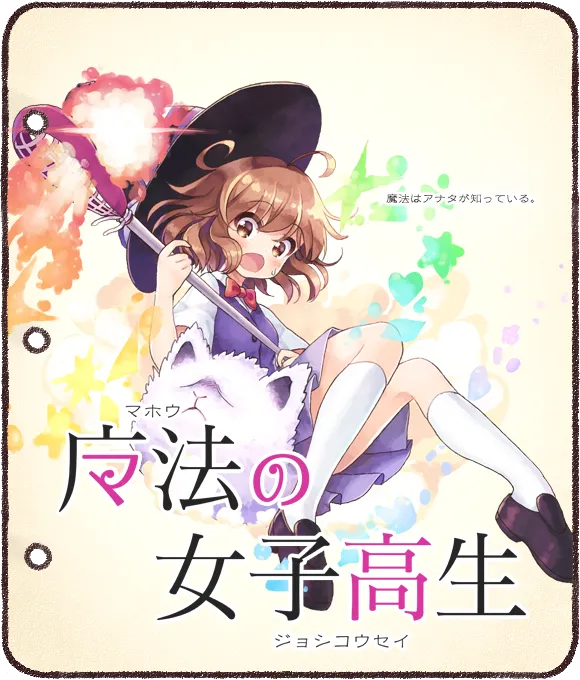
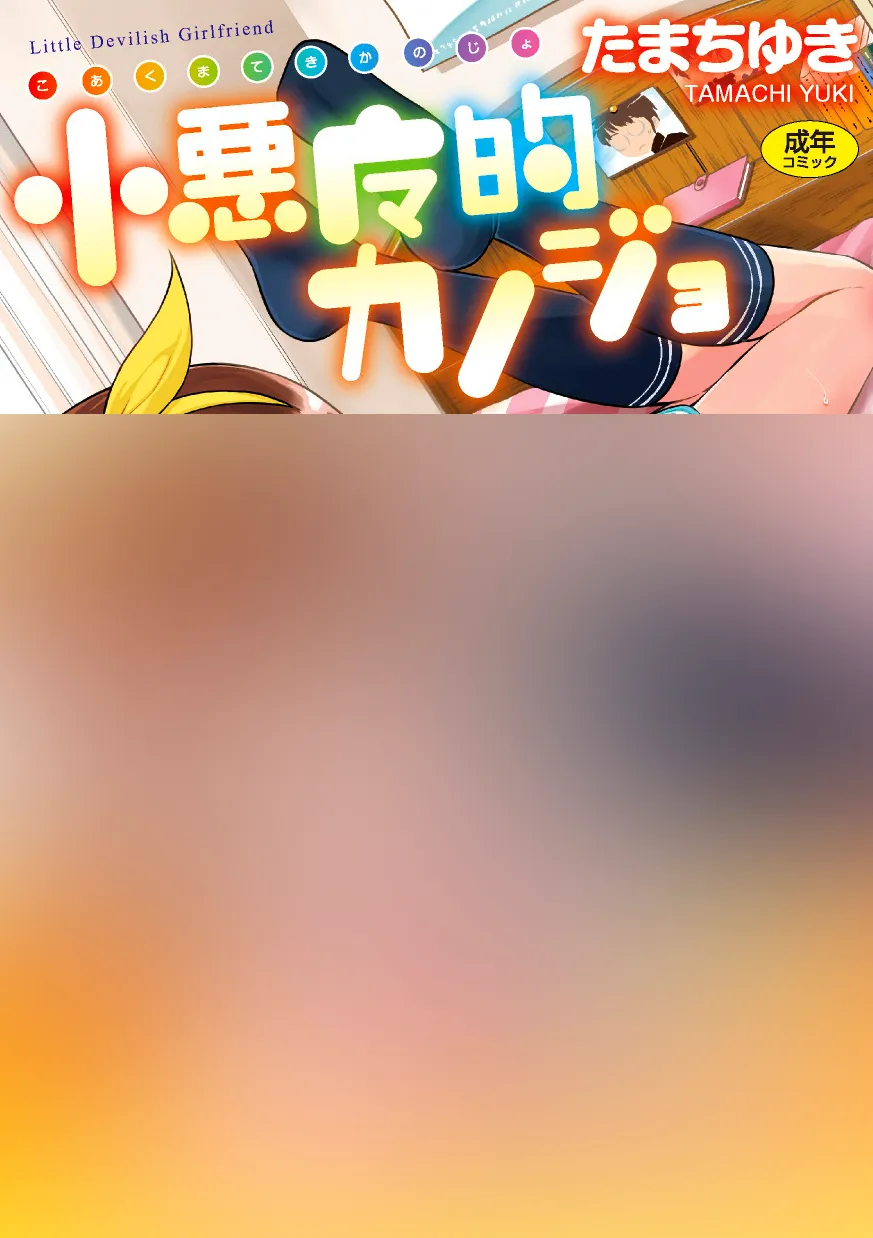
小悪魔的カノジョ
たまちゆきによる成年コミックで、茜新社の Tenma comics jc から2017年9月に出版された1。
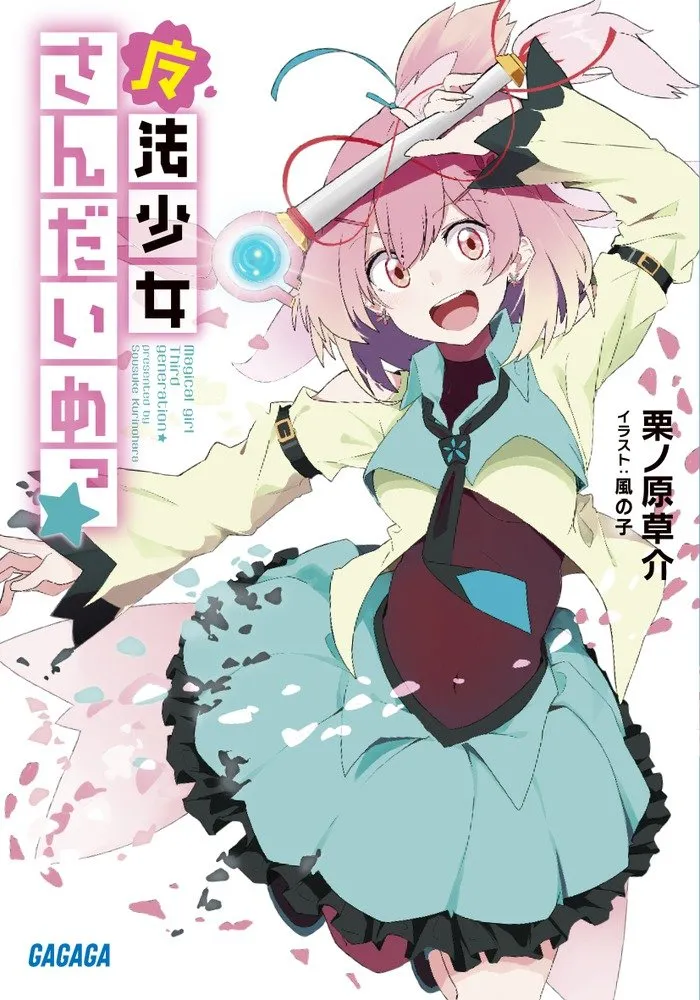
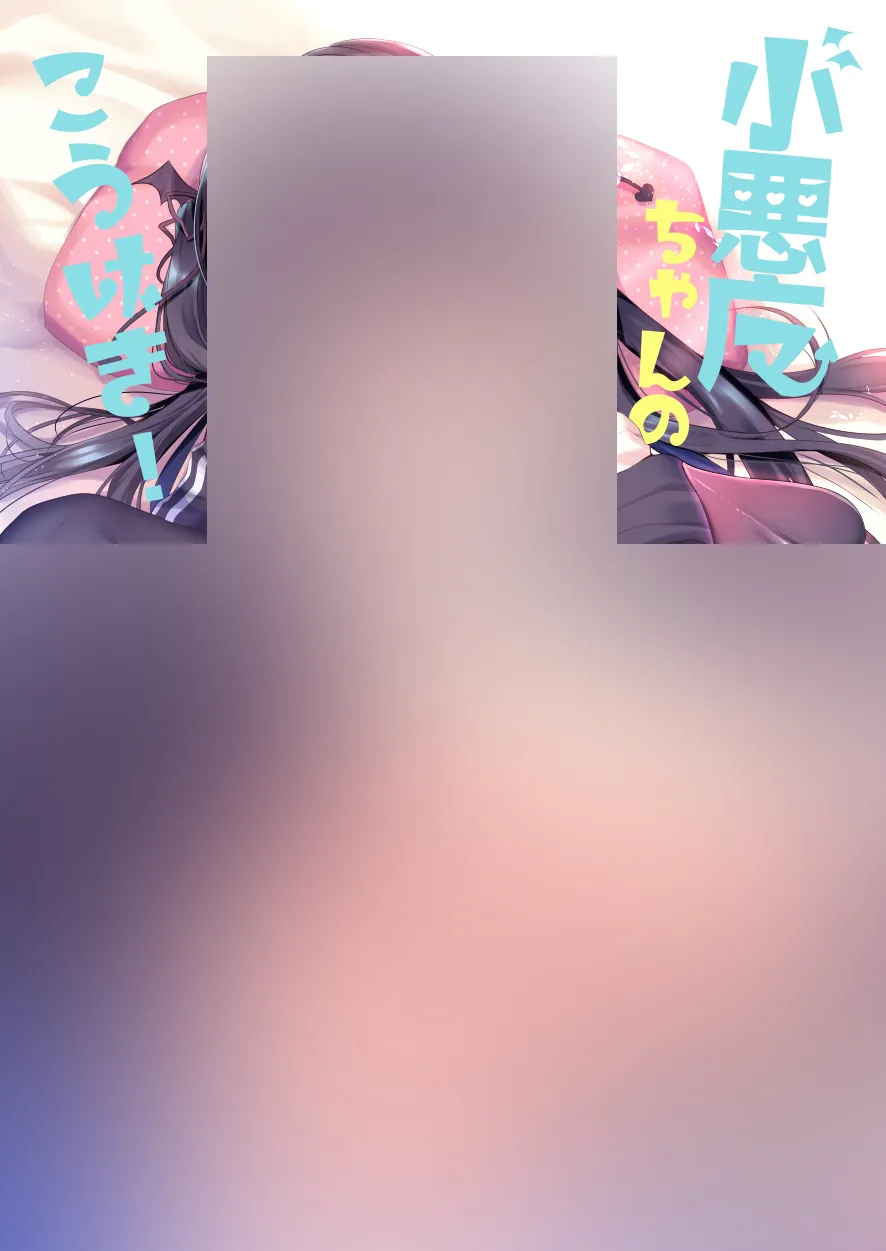
小悪魔ちゃんのこうげき!
あゆま紗由(サークル: ヤモセブン)による成人向けの同人誌で、COMIC1☆15 で頒布された。発行日は2019年4月29日、B5判・28ページ1。作者は頒布前に、pixiv にサンプルを公開した2。
2024年12月時点で、シリーズは8作目まで出ていた
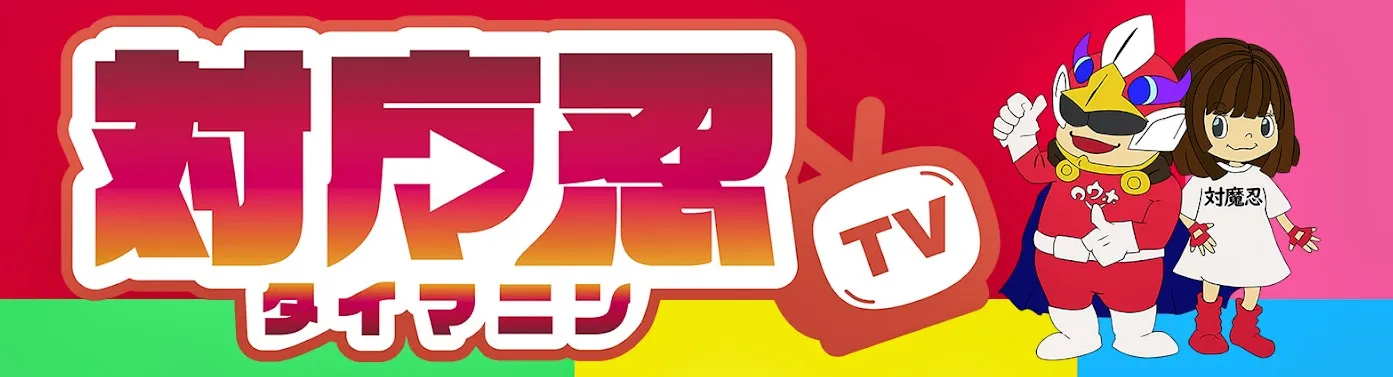
ゲー魔王
普津澤画乃新による漫画で、2022年9月29日に少年ジャンプ+(集英社)で連載が始まった1。マンガ家志望の唯野六(タダノロク)が主人公で、大ヒット中のゲーム「ゲー魔王」のアップデートによって世界が一変し、やり直しのできない、人生を賭けた超難易度のゲームが始まる1。
連載は完結しており、ジャンプコミックスは全5巻2。第38話「明日見えない僕たち」は2024年6月20日に公開された3。第1話の題「あした みえない ぼくたち」2と対になっている。
対魔忍サプリ 対魔忍アサギ Energy Supplement
「対魔忍」シリーズのキャラクター・対魔忍アサギを題材にしたサプリメント(マカパウダー含有食品)。販売元は株式会社omito で、「「3000倍のオトコになれ…!!」対魔忍がサプリとなって登場!」とうたう1。
対魔忍サプリには、続編の「水城ゆきかぜの雷撃energy」もある。
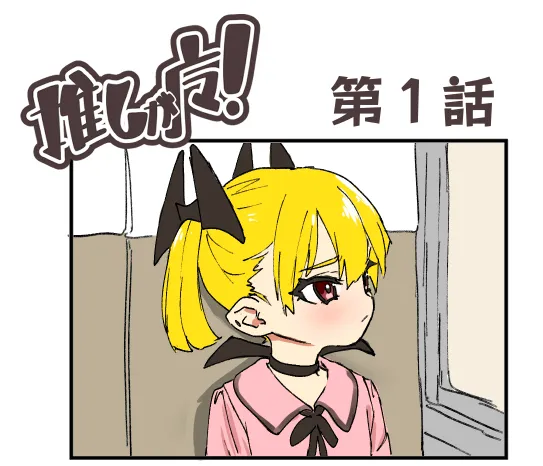
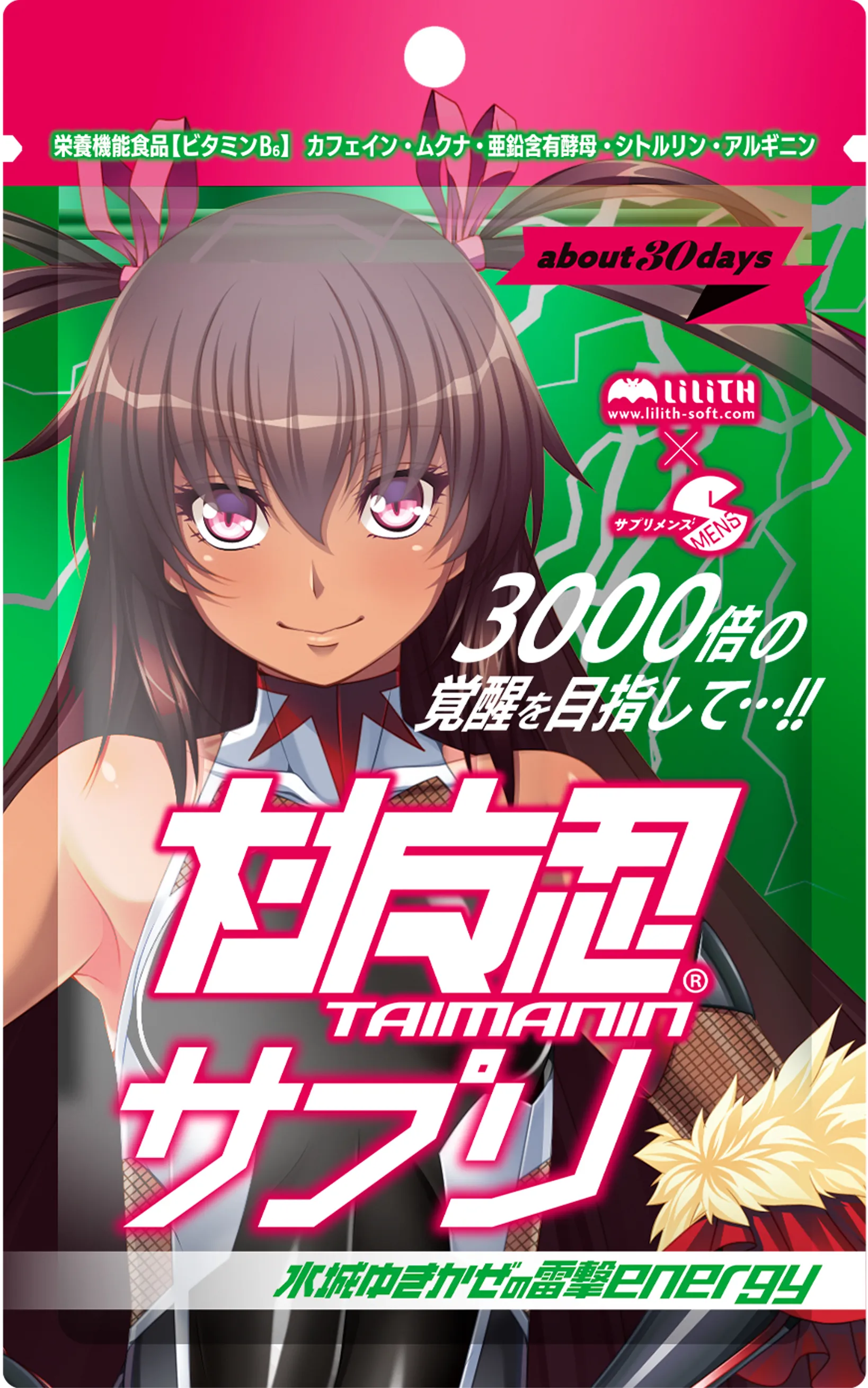
対魔忍サプリ 水城ゆきかぜの雷撃energy
「対魔忍アサギ Energy Supplement」の続編で、キャラクター・水城ゆきかぜを題材にしたもの。販売元は株式会社omito で、「爆発的人気となったあの「対魔忍サプリ」に続編が登場!!」とうたう1。ロゴの形は1作目と同じで、色が変わっている。
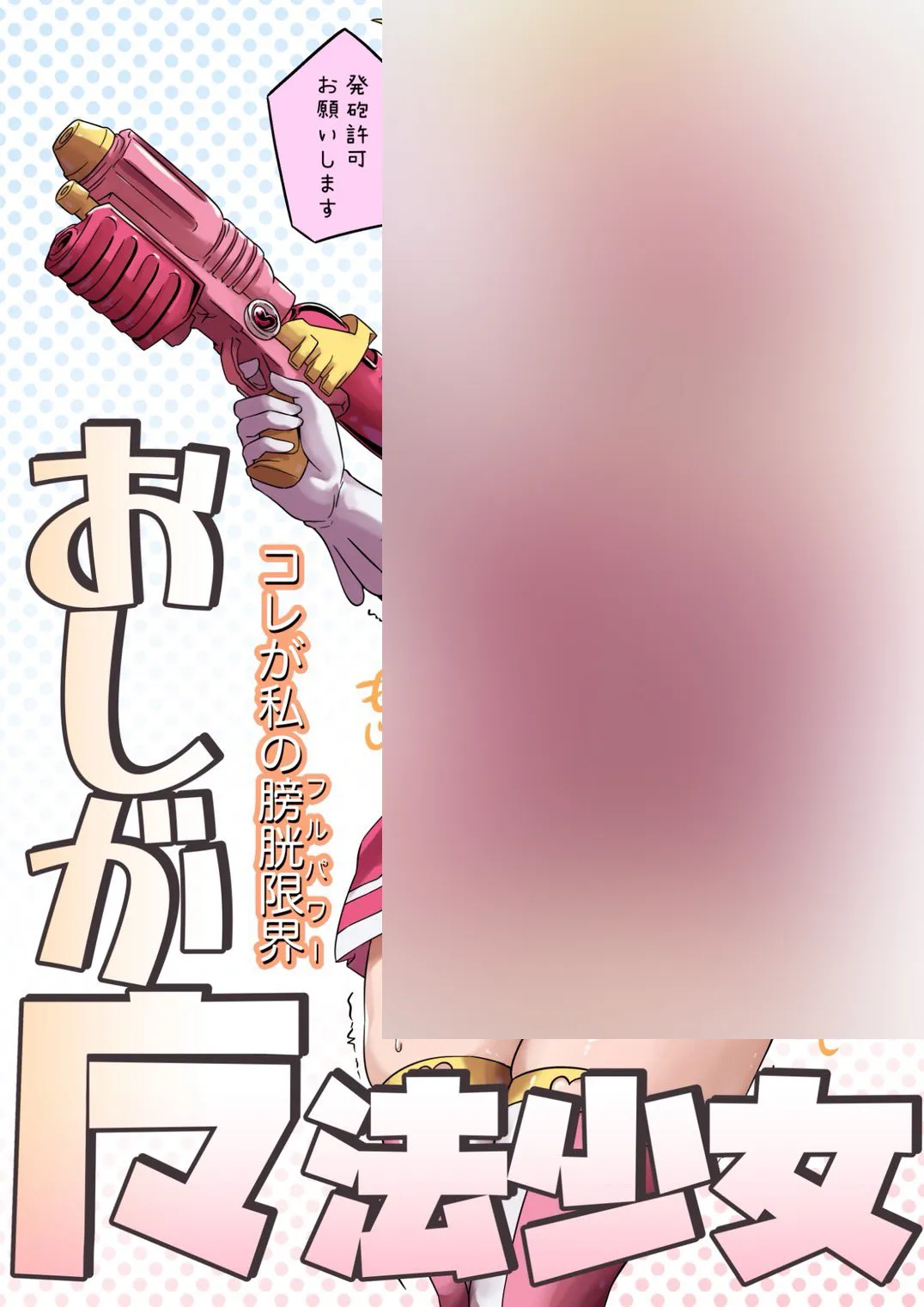
おしが魔法少女
秋野みゃじ(サークル: みゃ島)による成人向けの漫画(18ページ)で、2025年11月10日に pixiv で告知され1、同日に DLsite と FANZA で販売が始まった2,3。BOOTH でも販売された4。pixiv での作品名は「おしが魔法少女」、DLsite・FANZA・BOOTH での商品名は「おしがま魔法少女」。
ロゴは、フォント「オとマのペ」と「キルゴ」の組み合わせで作られている。「オとマのペ」は、漫画の描き文字をイメージしたかな文字のフォント5。X で両フォントの組み合わせかを尋ねたところ、作者から「キルゴはひらがながイメージと合わなかったから組み合わせたんでした」との回答があった6。
最古の記録(暫定)
略字の使用が確認できている、最も古い作品です。
バロム・1のファンだった少年・道雄の父親が、家族に宛てた手紙です。